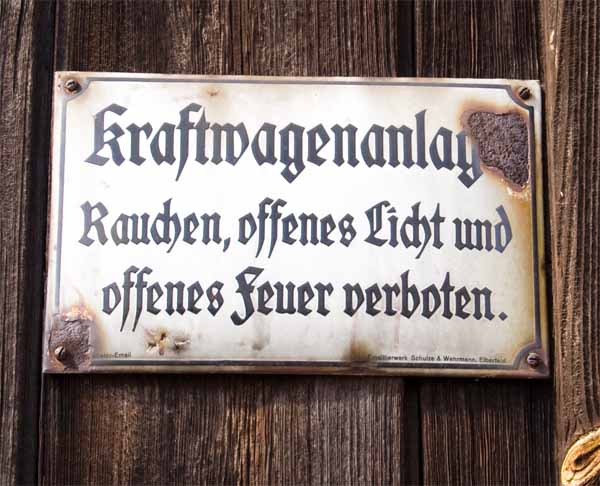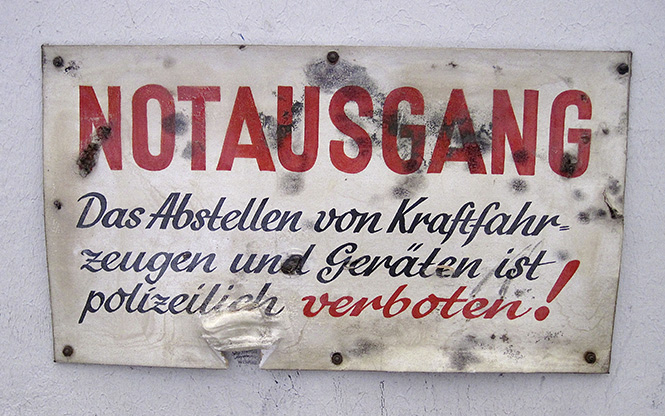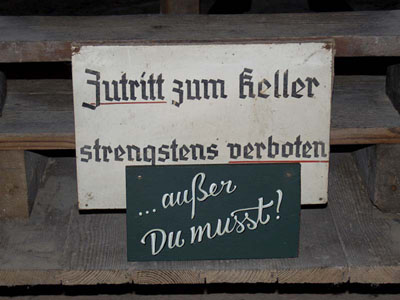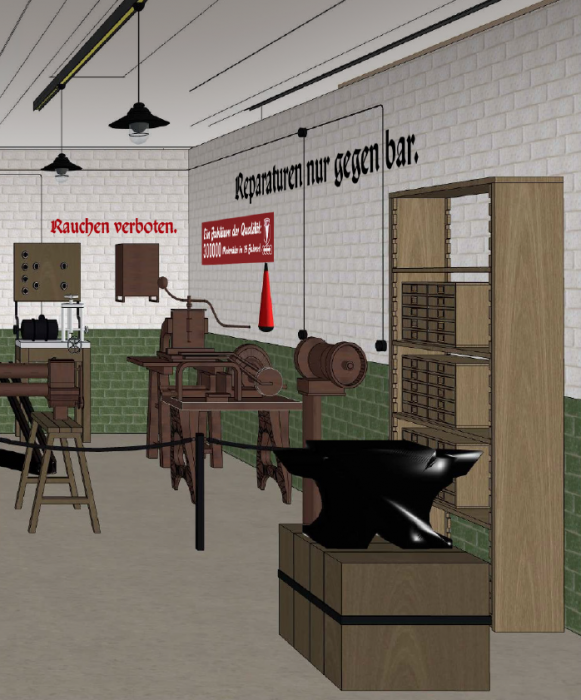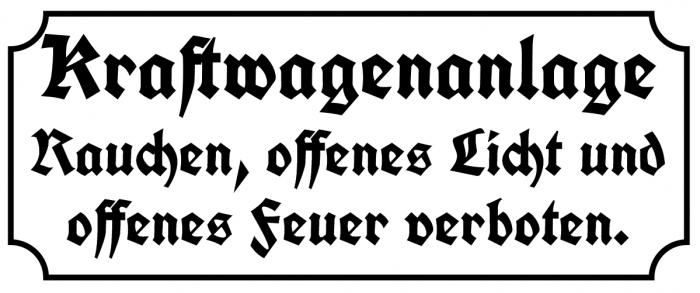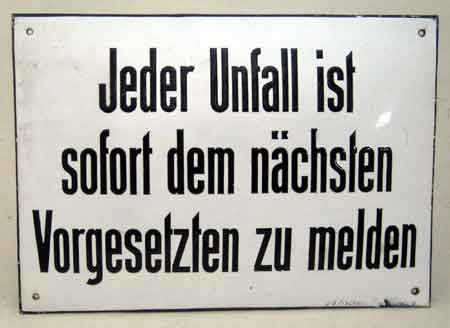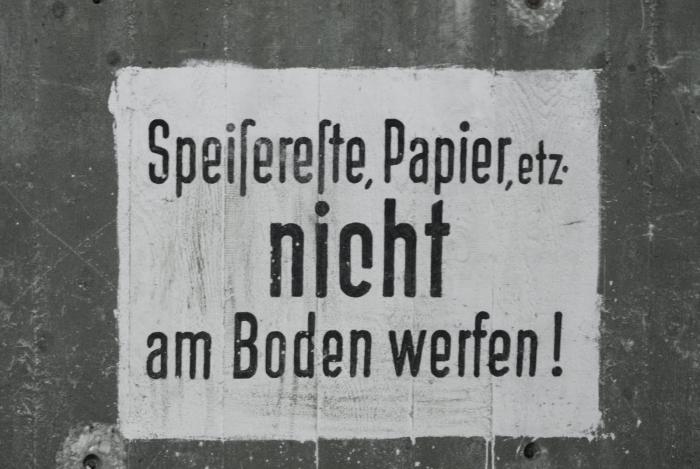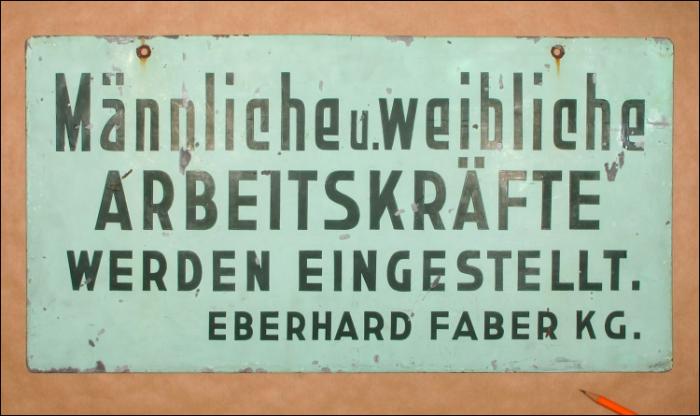
könnt Ihr eine lizenzfreie Fraktur empfehlen, wie sie in den 1930er Jahren verwendet wurde? Es geht um die Nachempfindung einer damaligen Auto-Union-Werkstatt.
Im Entwurf haben wir die San Marco verwendet. Aber ich denke mal, dass eine italienische Gebrochene für gothische Kathedralen nicht so das Richtige ist. Die Weiss-Gotisch aus Ralfs hilfreicher Zusammenstellung (1930er-Jahre-Schriften) habe ich mir schon angesehen, aber vielleicht gibt es noch andere nicht ganz so eckige Varianten.
Ich finde die Weiss-Gotisch schon ganz passend. In der gleichen Liste sind auch die Gotenburg und die Post-Fraktur, die gehen doch auch. Ich denke aber die Weiss-Gotisch ist gerade durch die kantigen Formen in diesem Fall am besten geeignet ist, da solche Schriften ja wenig künstlerisch sondern eher technisch klar geschrieben wurden – zumindest in solchen technischen Werk- und Produktionstätten.
Wir sind gerade dabei eine Mühle zu einem Kulturzentrum umzubauen und dort findet man noch Massenhaft Beschilderungen in gebrochenen Groteskschriften. Ein genaues Datum dazu habe ich zwar nicht, aber ich kann mir vorstellen, dass die zeitlich nicht allzu weit daneben liegen:
(Im Keller sind halt die Toiletten :tuschel: )
Allerdings wurde für Wandsnschriften, wie "Rauchen verrboten", Kraftwagenhalle" oder "Vorsicht beim laufenlassen von Motoren, Vergiftungsgfahr" oft keine Frakturschrift, sonden eine der DIN1451 ähnliche Schrift, die meiner Berlin Email sehr ähnlich sieht (wenn nicht oft genau so) verwendet. Gerade dieses weit heruntergezogene C sah man oft, da hier so eine Schablone (ohne die sonst üblichen Stege bei Schablonenschriften) sowohl für das c wie für das e verwendet werden konnte
Aber wieso geht es zum Keller die Treppe hinauf statt hinab?
Die beiden Schilder stehen so, dass man sie beim runtergehen sehen kann an der da drüber nach oben führenden Treppe angelehnt (bzw. das obere ist angenagelt)
Ähnlich, aber nicht ganz. Ich hab das mal in meiner KochFraktur UNZ1 nachgesetzt:
Könnte man natürlich nehmen, auch wenn ich der Meinung bin, dass es ein ziemlich übertriebenes Klischee ist, in allen Darstellungen, die im Deutschland der 1930er Jahre angesiedelt sind, überall markige Spruche in Frakturschrift anbringen zu müssen. Wer in die Zeut zurückversetzt würde, dürfte ziemlich überrascht sein, wie wenig Fraktur so im Straßenbild zu sehen war. Fraktur war mehr die Schrift für alles gedruckte, von Büchern, uber Zeitschriften bis hin zu Plakaten.
Gerade Warnhinweise in Werkstätten wurden dagegen eher selten von richtigen Schildermalern gestaltet, wenn hier nicht Emailschilder verwendet wurden, war es eher das Werk einfacher Malergesellen, oder man verwendete Blech-Schablonen, bei denen dann die Stege nicht selten von Hand nachgepinselt wurden.
Pachulke, ist das die Deutsche Schrift von Rudolf Koch?
Keine Ahnung, ich habe das nur in Beelitz photographiert.
Gerade Warnhinweise in Werkstätten wurden dagegen eher selten von richtigen Schildermalern gestaltet, wenn hier nicht Emailschilder verwendet wurden, war es eher das Werk einfacher Malergesellen, oder man verwendete Blech-Schablonen, bei denen dann die Stege nicht selten von Hand nachgepinselt wurden.
Sieht man ja bei meinem Beispiel auch. Das war bestimmt kein richtiger™ Schildermaler – aber dennoch gebrochen  8-)
Ich habe ja auch nicht gesagt, dass NIE Frakturschrift verwendet wurde, sondern nur eben erheblich seltener, als man es z.B. in US-Filmen sieht, die im Deutschland der 1930er Jahre spielen, aber da läuft ja dann auch mindestens ein Deutscher in Lederhosen herum.
Vielen Dank Euch allen für die tatkräftige Unterstützung! :-P Zur Zeit tendiere ich zur Weiss-Rundgotisch, Lindenthal (Catfonts guter Tipp!) bzw. Gotenburg, Steffmann (Danke Schnitzel, die habe ich ganz übersehen).
Und nebenbei bemerkt: es geht nicht um Schilder, sondern wie oben abgebildet um eine Wandbeschriftung.
Ich kenne Steffmanns Gothenburg, schließ´lich hab ich sioe ja mit Erlaubnis von Herrn Steffmann um Ligaturen erweitert. Diese ist aber leider deutich eine Autotrace-Schrift, bei der so einige Konturen etwas "ulkig" sind. bei relativ kleinem Text mag man das nicht so sehen. Vielleicht ist ja meine Blankenburg was, die habe ich nämlich direkt gezeichnet, und hat dadurch geradere Konturen.
Wäre Schreibschrift eine Möglichkeit? Wobei dieses Schild bestimmt jünger ist:
Hallo Kathrin, Danke auch für Deine Anregung! Eine Schreibschrift setzen wir an andere Stelle ein, ebenso eine Grotesk. Für diese Raumsituation (siehe oben) haben wir uns unter anderem an folgender Fotografie orientiert – und es kommt ja nicht so oft vor, dass man sich auch mal an den Reizen einer Fraktur erfreuen und diese einsetzen kann. ;-)
Und ich kann zur Schrift nur sagen: irgendwas Frakturiges, das ein Schildermaler sich aus dem Pinsel geschüttet hat. Mit Sicherheit keine Satzschrift.
Ich habe diese Schrift (noch?) genau so nicht, habe bnei mir aber mal nach dafür verwendbarem geguckt. Ein paar davon hab ich grad in der Mache:
Danke Catfonts! Ja ich hatte mich inzwischen auch die Weiss Rundgotisch und die Grobe Deutschmeister heraus gepickt. Aber die Koch könnte natürlich auch gut passen … ;-)